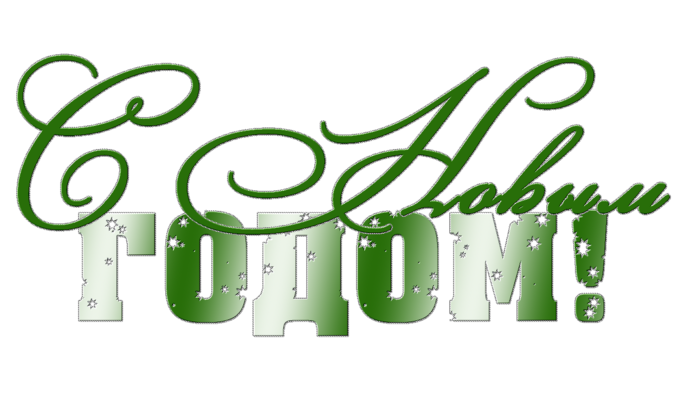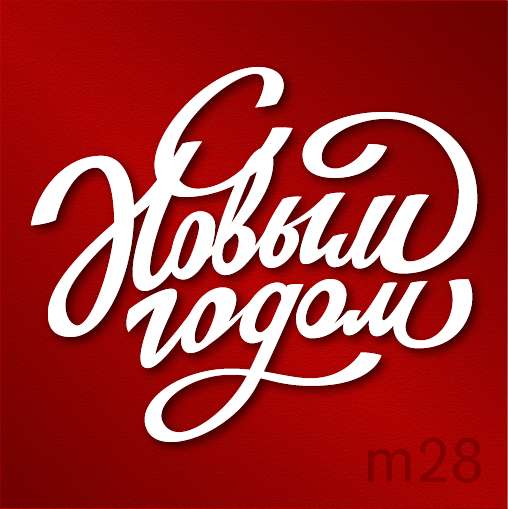
Написать с новым годом красивым шрифтом. Красивые надписи с новым годом
На этой страничке собраны все самые красивые надписи «С Новым годом!» на прозрачном фоне. То, что надписи на прозрачном фоне, означает, что их можно использовать для своих календарей или открыток с фоном любого цвета.
Голубая надпись с Новым годом
И первая надпись выполнена в голубом стиле, со снеговиком, снегуркой и шапкой. Эта надпись с прозрачным фоном. Высокое разрешение этой надписи позволяет ее использовать в макетах большого размера. Скачать бесплатно можно в формате PNG .
Рукописная надпись с Новым годом
Эта надпись С Новым Годом написана красивым рукописным шрифтом. Буквы разукрашены градиентом, от голубого до коричневого. Размер надписи довольно таки не большой, но если вам нужно оформить открытку или календарь А4 формата, то вполне сгодится. Скачать надпись .
Сборник красивых надписей с Новым годом
Представлена коллекция из одиннадцати надписей разного типа.
Все надписи на прозрачном фоне. Размер разный, но в большинстве надписи имеют высокое разрешение. С их помощью вы можете оформить открытку или календарь на любой год, так как год в надписях не указан. Скачать сборник .
Надпись С Новым годом из ткани
Данная надпись выполнена на прозрачном фоне, и имеет эффект букв, выполненных из ткани. Скачать бесплатно можно в формате .
Желтая (золотая надпись) на прозрачном фоне
Готовую надпись можно повесить отдельно, когда большими буквами на картоне или длинном листе ватмана изображено? «С Новым годом!» или дополнить ею плакат. Внизу под заголовком на расположить разные картинки или стикеры. Иногда подобные надписи украшают таблички с фотографиями сотрудников. На окно подобные надписи вешают чаще в магазинах, красивой стороной наружу.
Дома тоже можно украсить свои окна подобным образом, ведь позитивная надпись всегда поднимет настроение. Интересно, что купить ее можно в отделах для оформления подарков, где продают канцелярские принадлежности, но действительно большая и красивая готовая для вывески надпись встречается редко.
Буквы либо слишком мелкие, либо сама надпись маленькая.
Можно заказать ее в полиграфии, но там есть ограничения в размере. Обычная полиграфия редко выпускает большие форматы, для нее максимум – это А3. Можно конечно заказать десяток листов А3, где на каждом будут готовые шаблоны букв. Потом останется вырезать их и собрать готовую надпись. При этом шрифт, цвет его и оформление клиент выбирает сам. Иногда некоторые организации заказывают открытки и вытынанки. Дизайнеры сами рисуют их через специальные программы.
Можно найти готовые надписи и отдельные буквы в сети самостоятельно. Если вам необходима огромная готовая надпись, возьмите большие листы и срисовывайте вытынанки, ориентируясь по распечатанным шаблонам. Вам придется заранее просчитывать размеры всех букв, расстояния между ними, также возможные узоры и другие особенности оформления уже готовой надписи.
На Новый год 2019 большие плакаты потом вешаются в коридорах.
Небольшие надписи
Для них скаченные вытынанки переводятся в натуральной величине. Шаблон просто прикладывается к новому листу, обводится. Готово. Останется только раскрасить фломастерами или красками. Очень удобно, когда к празднику нужен небольшой плакат с красивой надписью сверху. Иногда буквы распечатываются через цветной принтер и просто вклеиваются без срисовывания. Тогда становятся готовыми отдельными буквами в плакате или целой надписью.
Трафареты букв часто применяют в оформлении ресторанов и кафе, ведь люди будут снимать их для корпоративов и им захочется побыть именно в новогодней обстановке. Как здесь обойтись без надписей, шаров, колокольчиков? Менеджеры поручают сотрудникам быстро и красиво оформить залы, особенно когда они уже сняты и гости ожидаются. Выбрав готовые вытынанки для вырезания, сотрудники распечатывают их сначала на простой бумаге, затем подбирают красивые разноцветные листы, на которые перенесут шаблоны.
Обычно распечатываются отдельные буквы, и порой их требуется много, ведь в большом зале одной надписи недостаточно. Выкройка берется одна для всех надписей, чтобы соблюдать единую композицию в оформлении. Конечно, Новый год не требует официальности, наоборот, в оформлении важно сделать зал красивым и ярким, но не безвкусным, чтобы клиенту было приятно находится внутри. Сотрудники предпочитают готовые шаблоны, чем рисовать самим. Это много времени, не факт, что в коллективе найдется хоть один приличный художник. Ведь красиво писать объемные, большие буквы тоже уметь надо.
На чем можно изобразить надпись?
Фантазии в этом плане нет границ. Многие дизайнеры используют большие праздники как источник хорошего заработка. Например, работники полиграфии. Вот Новый год, люди ищут красивые вещи, милые сувениры, которые можно подарить кому-то или оставить себе.
Футболки – изображение нового символа или праздничной надписи. Оригинальный, веселый подарок.
Новая футболка со смешным рисунком лишней не будет в любом гардеробе. Носить дома или на спорт, зато память.
Рукописный шрифт Alexandra
Каллиграфия очень популярна в дизайне татуировок, поэтому покажите всем ваши любимые цитаты с помощью этого элегантного шрифта. Этот шрифт выполнен в современном дизайне с плавными линиями и очаровательными изгибами, включает в себя все символы, которые могут понадобиться в тату-дизайне.
Шрифт Black Heat
Black Heat — это современный шрифт, созданный по мотивам викторианской эры дизайна. Скачайте этот полный сет цифр, букв и дополнительной поддержки для международных символов.
Шрифт Stay High